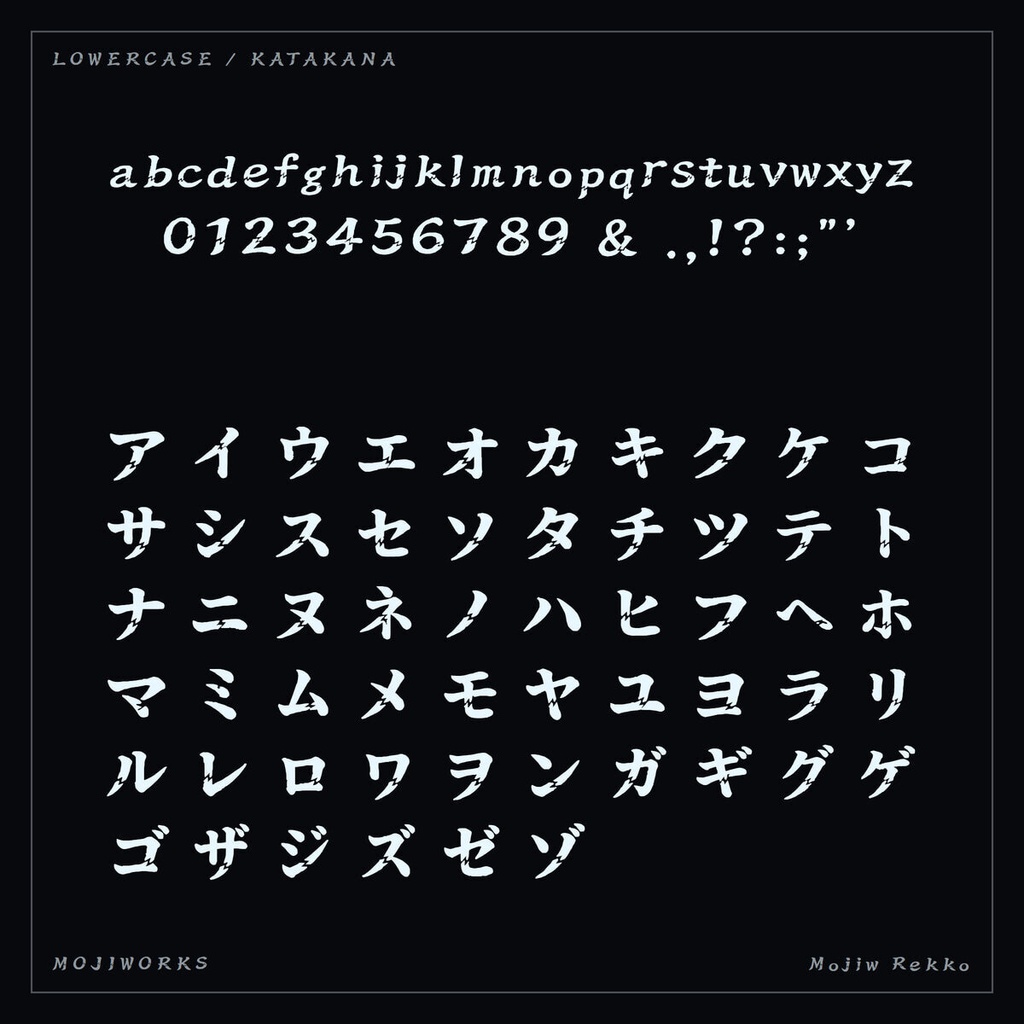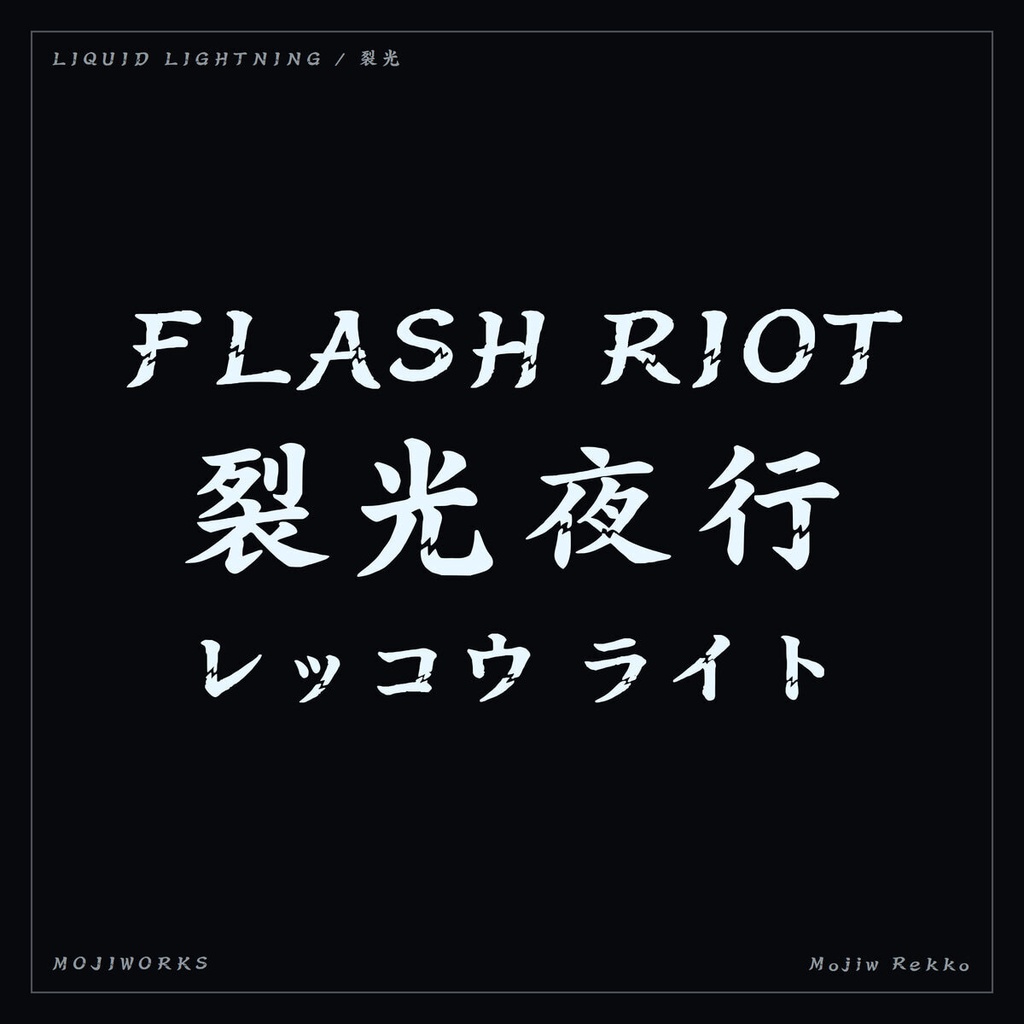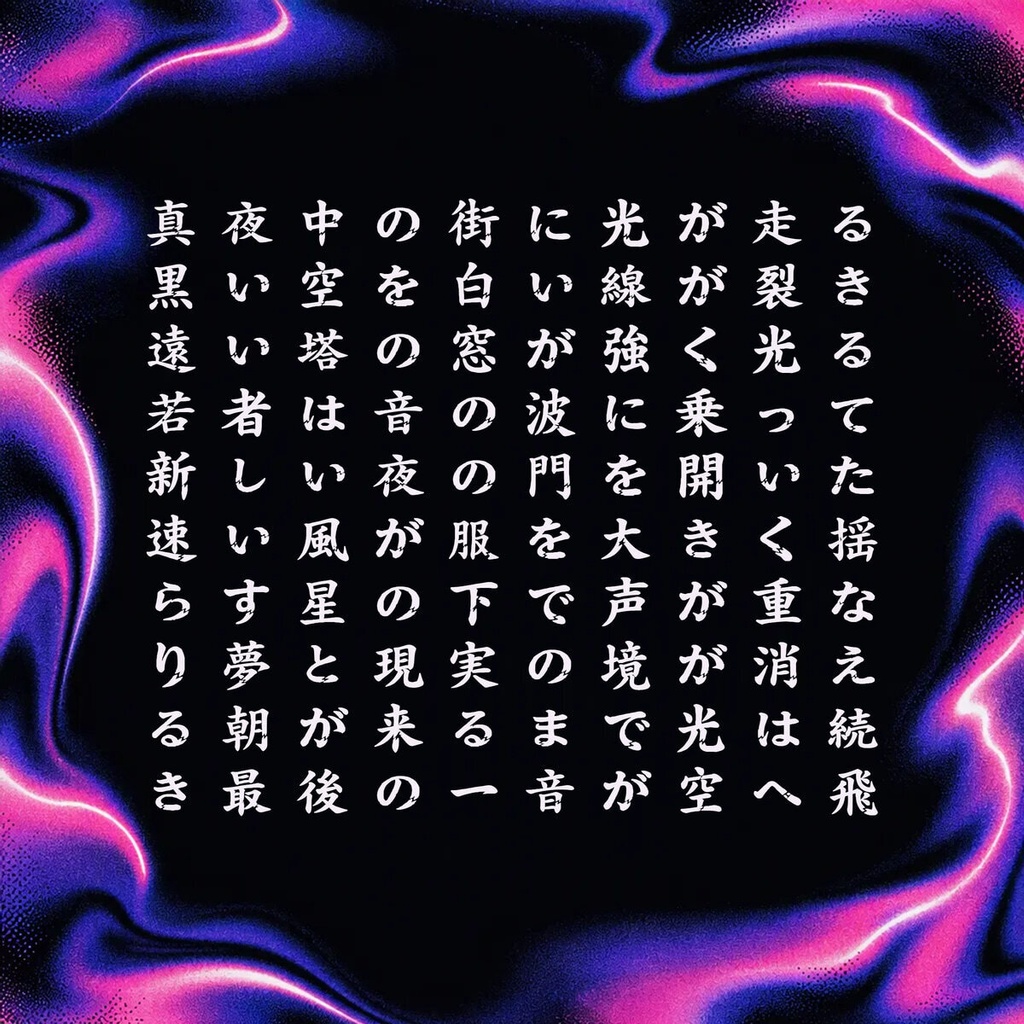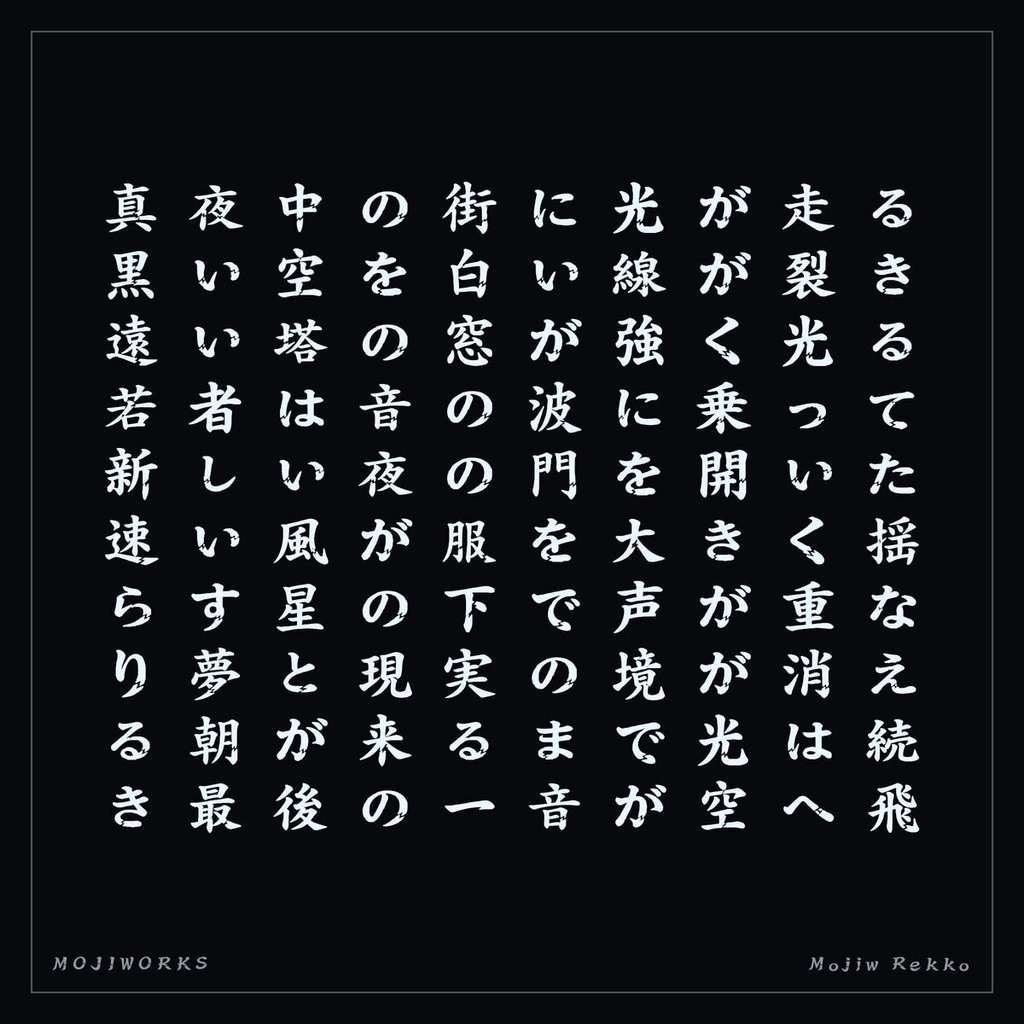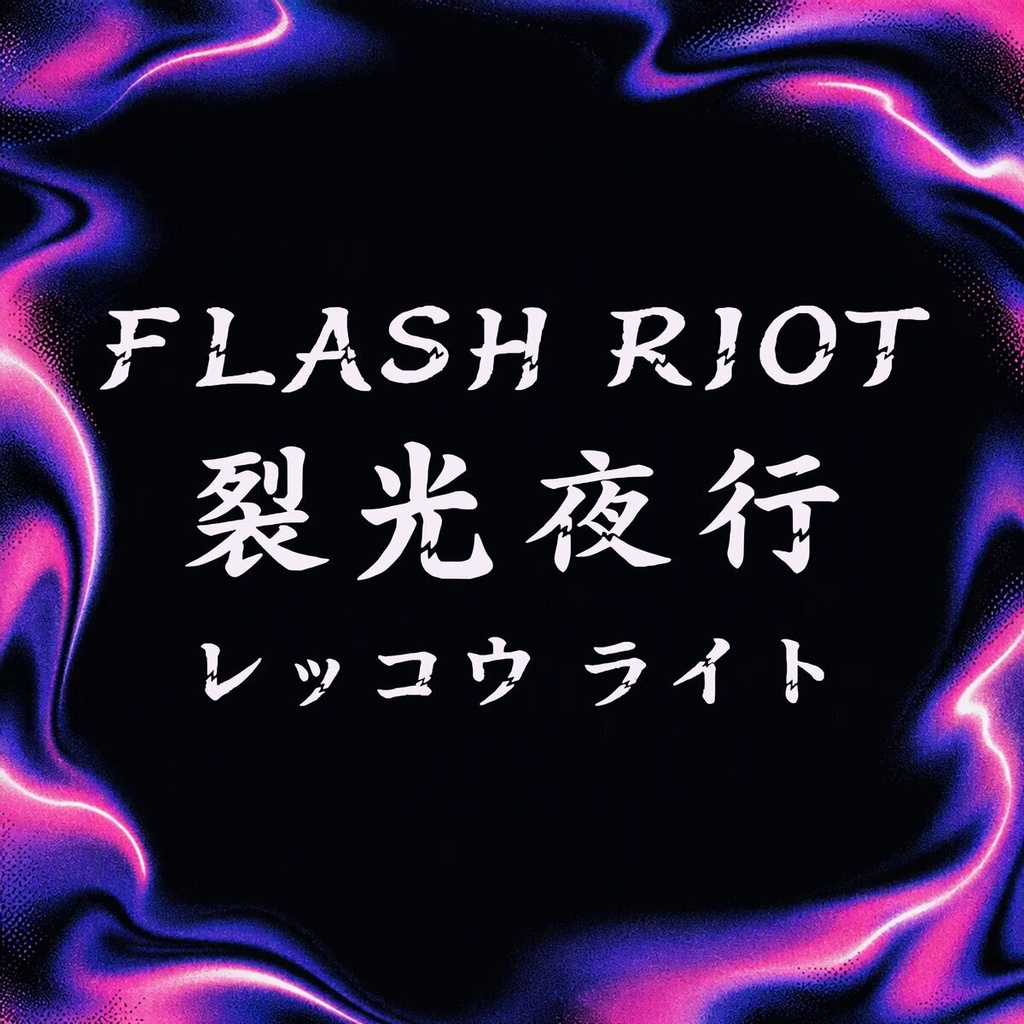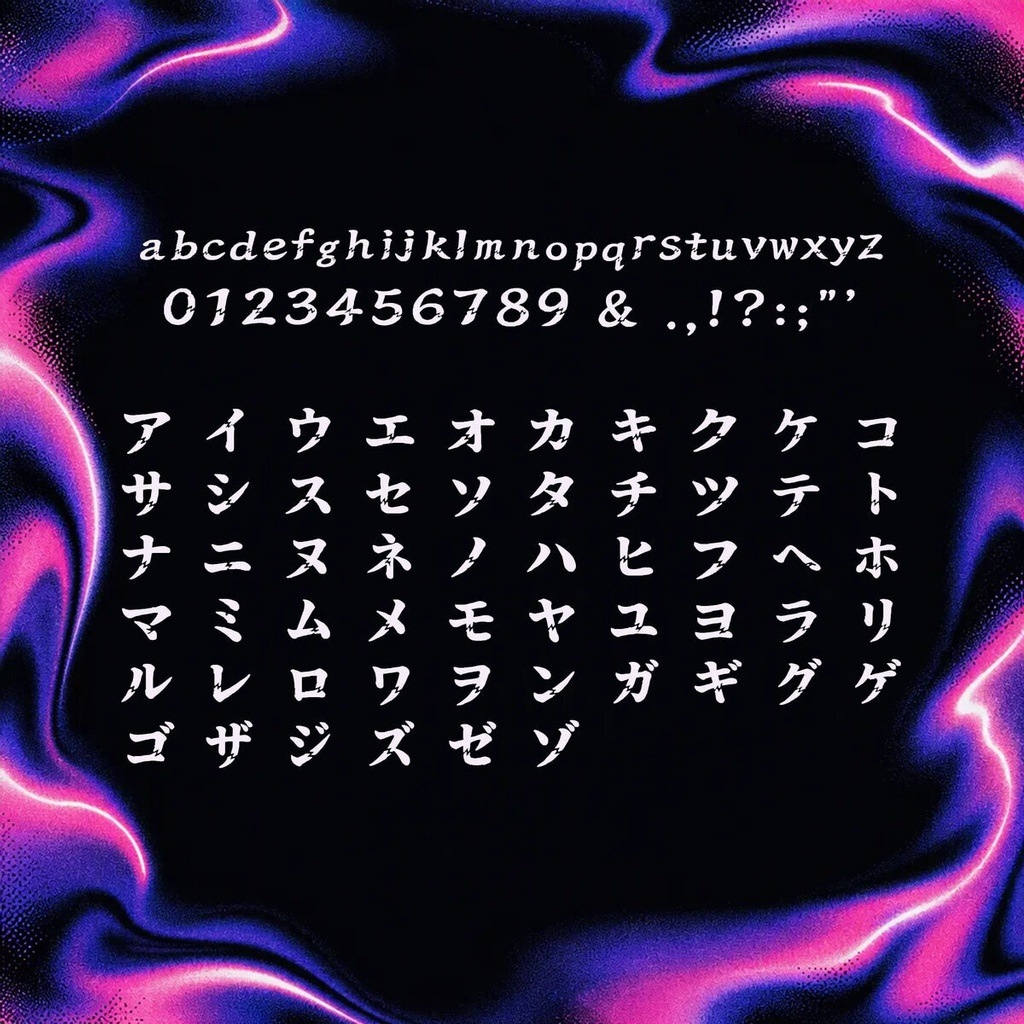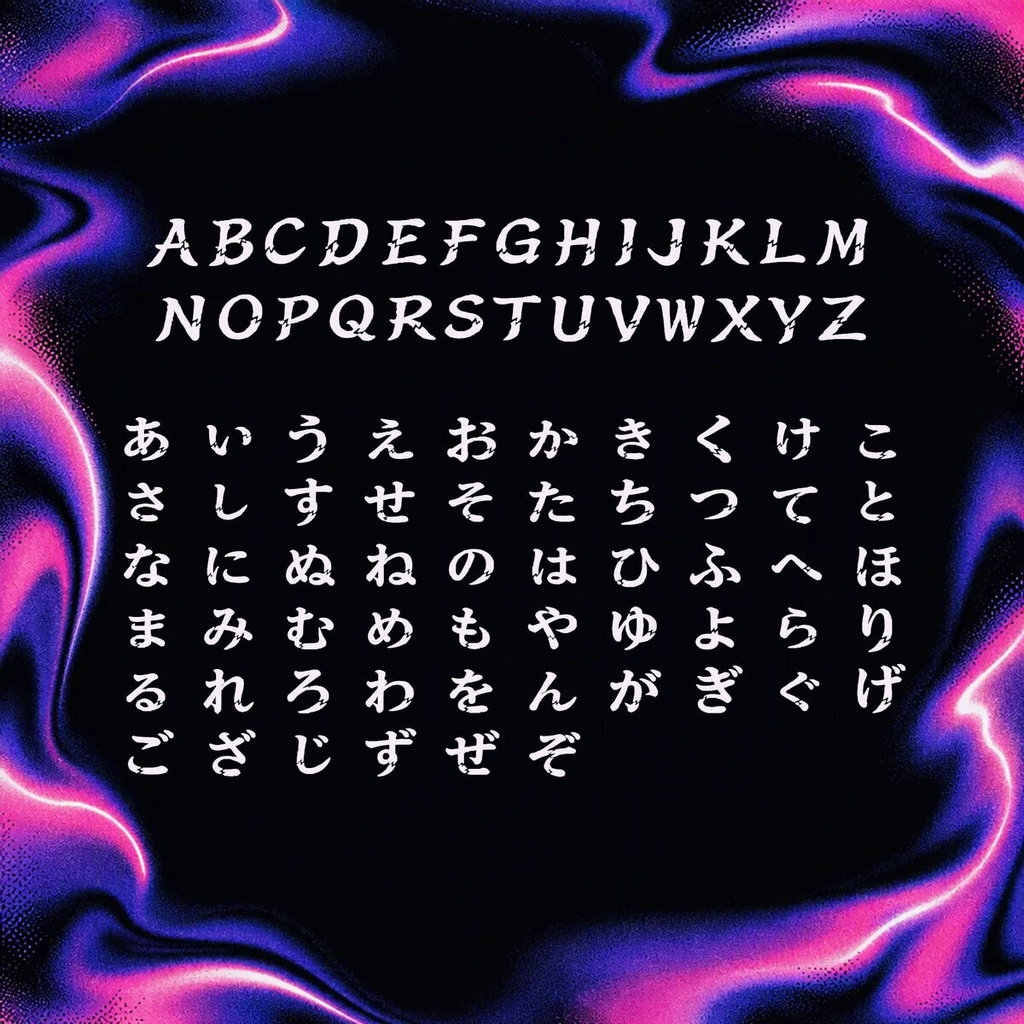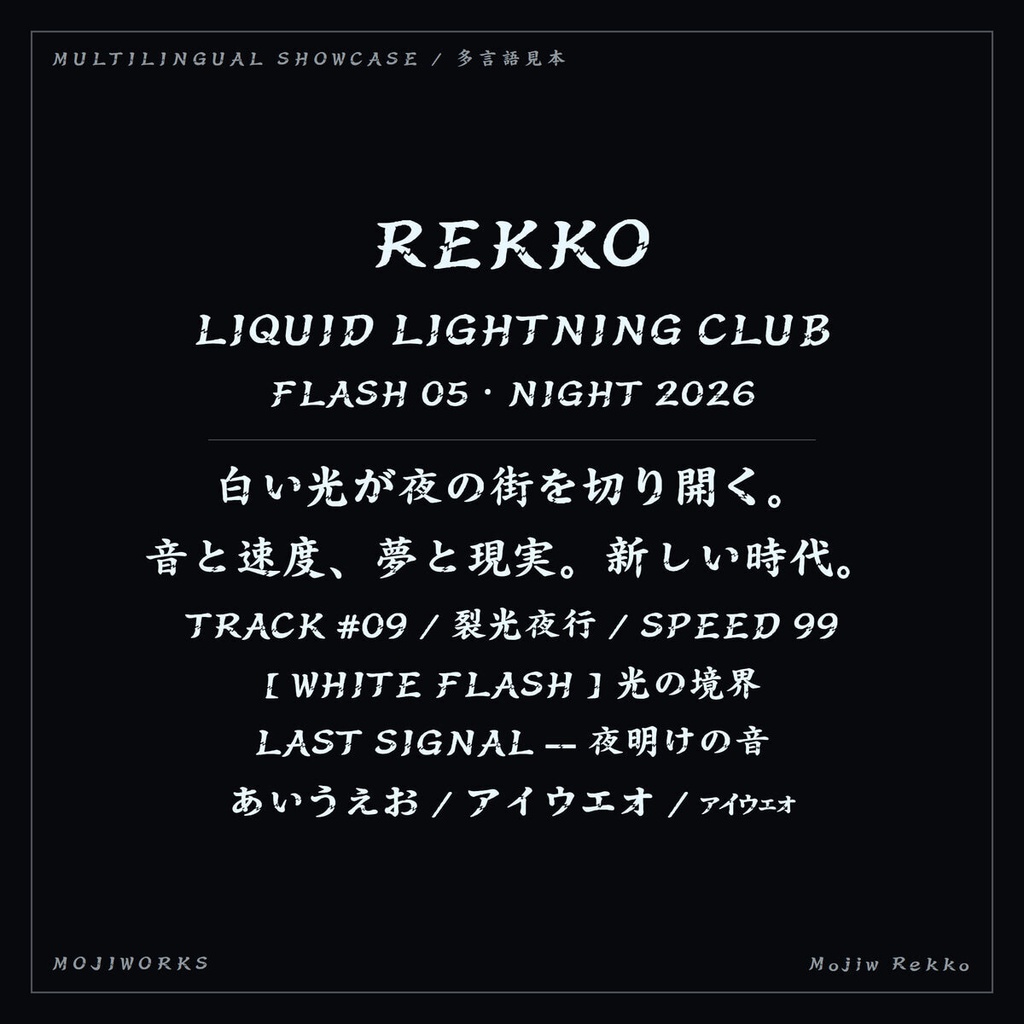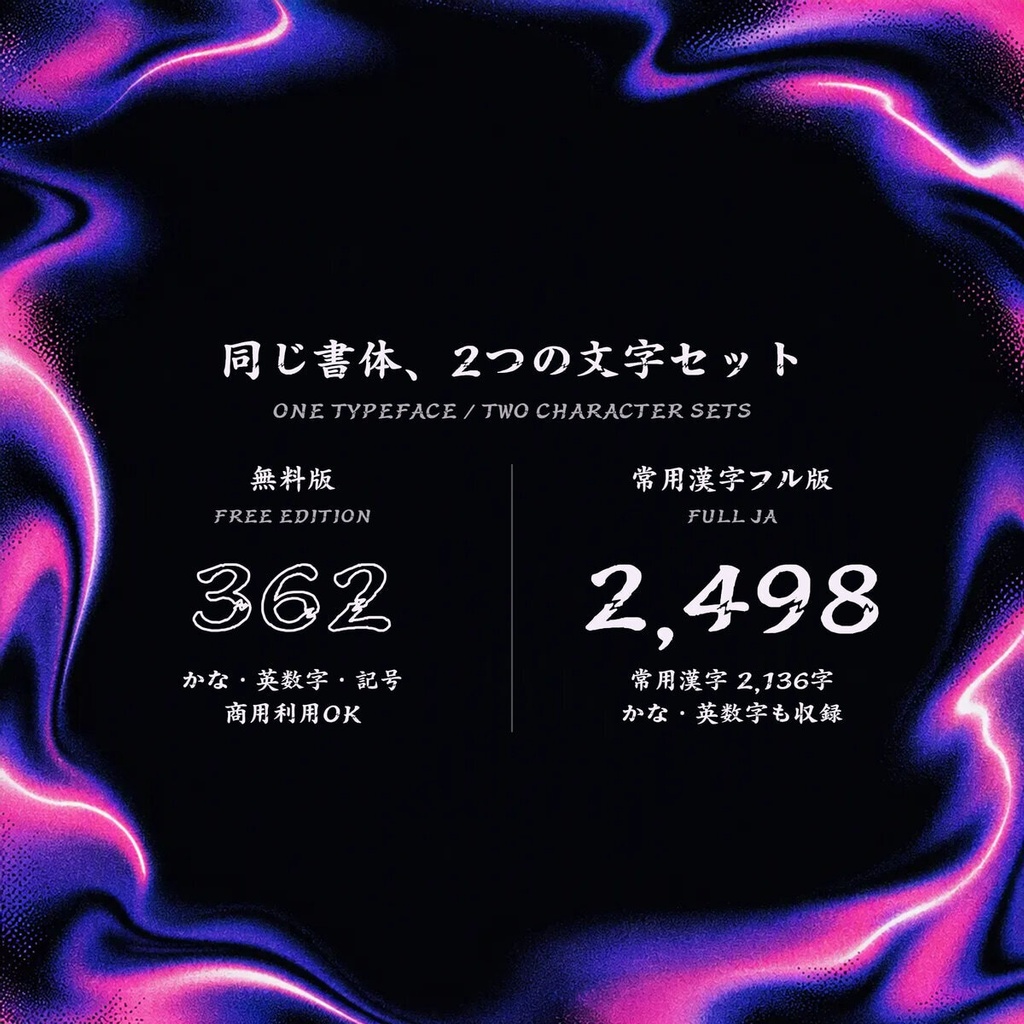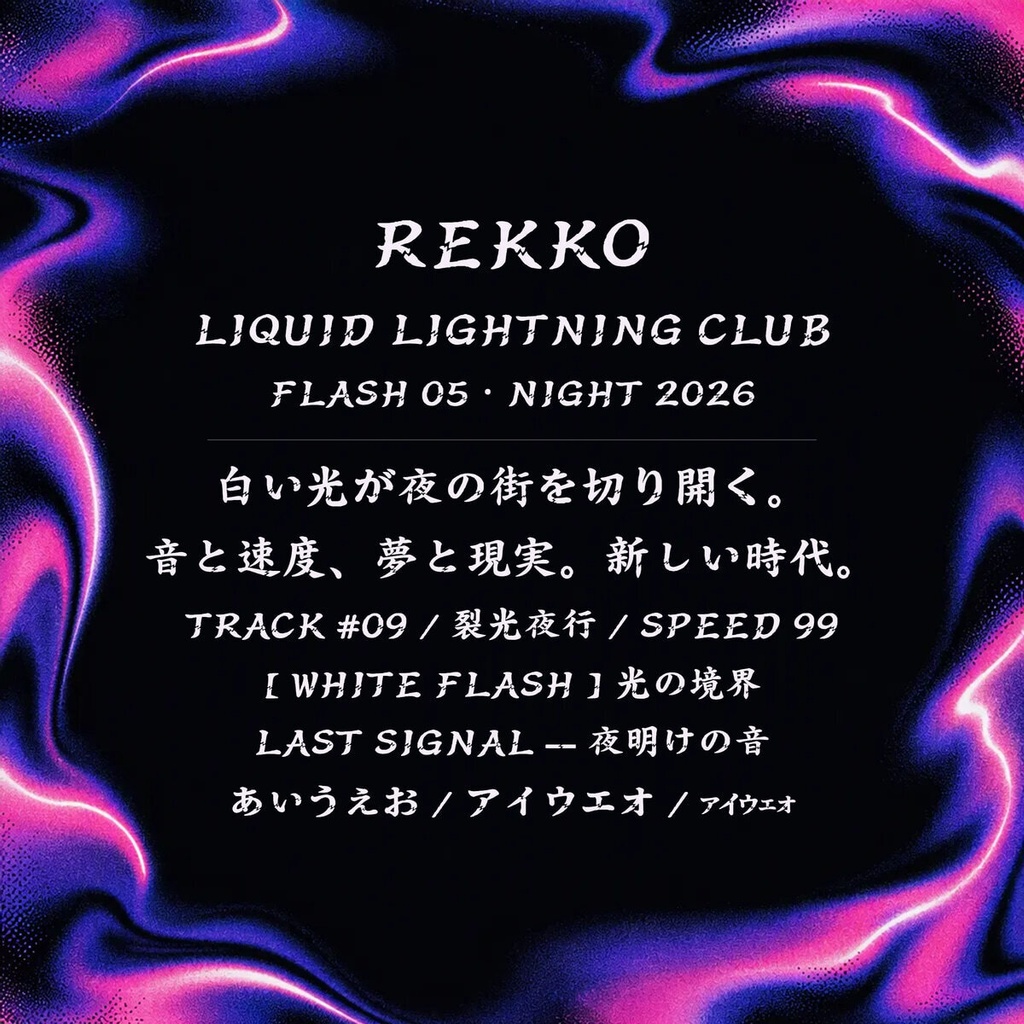
裂光 Rekko【フォント】 — 液体稲妻のY2K書体|常用漢字2,136字
液体のような輪郭を白い稲妻が走る、Y2Kディスプレイ書体です。 A liquid Y2K display face split by bright lightning seams. 【用途 / Use】 音楽ロゴ / ファッション / MV / ゲームタイトル / イベント For music logos, fashion, music videos, game titles, and events. 【常用漢字フル版 / Joyo Complete】 常用漢字2,136字を完全収録し、ラテン文字・ひらがな・カタカナ・記号を含む全2,437文字を収録しています。半角カナは収録していません。 Includes all 2,136 Joyo kanji and 2,437 characters total, including Latin, hiragana, katakana, and punctuation. Half-width kana are not included. 2437文字 / characters 【関連する収録版 / Other Edition】 ラテン文字・かな・記号を収録したスタンダード版もあります。 The Standard edition includes Latin, kana, and punctuation. ▶ スタンダード版 / Standard: https://mojiworks.booth.pm/items/8826755 【フォント仕様 / Specification】 バージョン / Version: 1.0.1 形式 / Format: TrueType (.ttf), Web (.woff2) 対応環境 / Platform: Windows, macOS, web browsers 収録字一覧 / Character list: CHARSET.txt 同梱 / Included: font files, README, LICENSE, character list, portfolio PDF, product previews. 【利用規約 / License Summary】 個人・商用利用可。1ライセンスは購入者1名に適用されます。 Personal and commercial use is permitted. One license covers one purchaser. 印刷・動画・ロゴ・グッズ等の静的成果物、および購入者が運営するサイトでの同梱WOFF2の利用が可能です。 Static output such as print, video, logos, and merchandise is permitted. The bundled WOFF2 may be used on a website owned or operated by the purchaser. ゲーム・アプリへの組み込みは、利用者が生のフォントを抽出できない形式に限ります。生のフォントを同梱する場合は別途ライセンスをご相談ください。 Game/app embedding requires protection against extraction of the raw font. Contact us for a separate runtime-embedding license when shipping raw font files. 標準ライセンスは1製品・1サイトあたり年間約100,000ユーザーまで。従業員50名超の組織を含む大規模利用は要相談。 Standard coverage is approximately 100,000 users per product/site/year. Larger use and organizations with more than 50 employees require an extended license. フォント本体の再配布・販売・貸与・変換・グリフ抽出・派生フォント制作・生成AI学習やスタイル参照は禁止です。 Redistribution, resale, lending, conversion, glyph extraction, derivative fonts, and generative-AI training or style reference are prohibited. 完全な利用条件は同梱の LICENSE.txt / LICENSE.jp.txt をご確認ください。 The bundled license files are authoritative; consult them for the complete terms. 【ほかのフォント・カスタム制作 / More Fonts and Custom Work】 フォント一覧、オーダーメイド書体、文字追加、拡張ライセンスのご相談はこちら。 Browse our catalog or contact us for custom typefaces, added characters, and extended licenses. https://mojiworks.booth.pm/